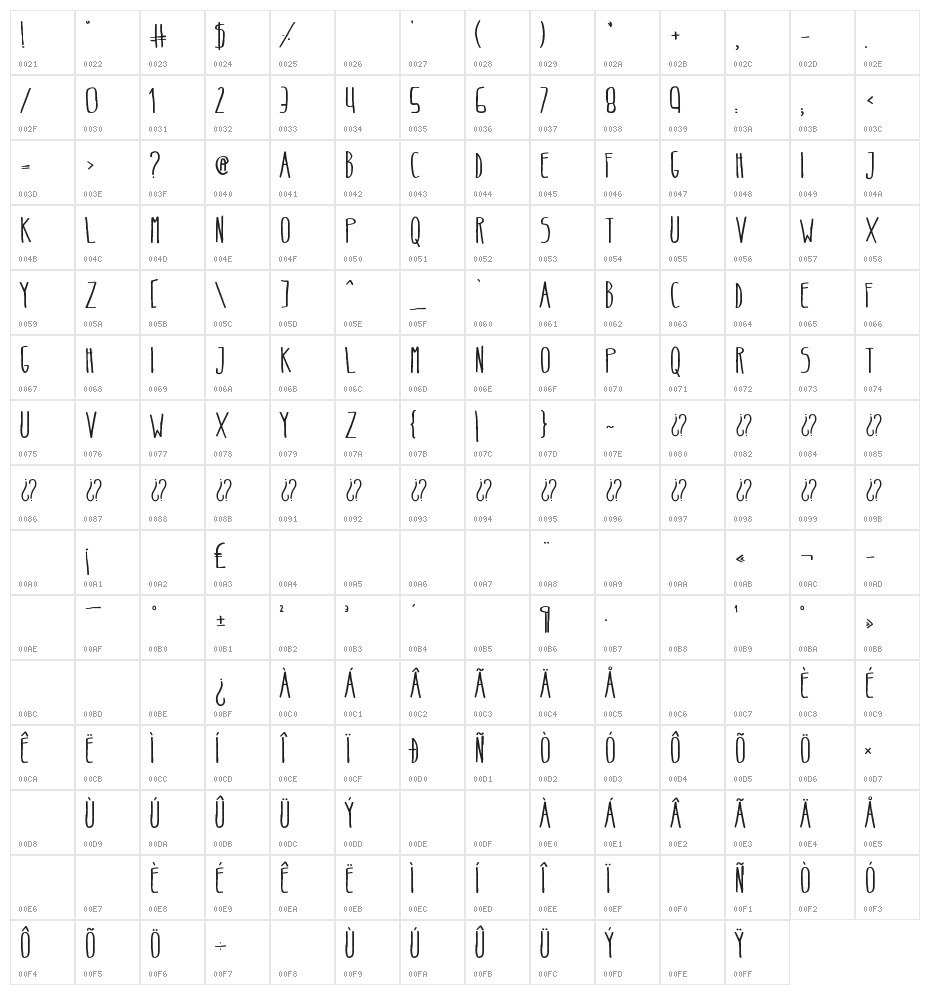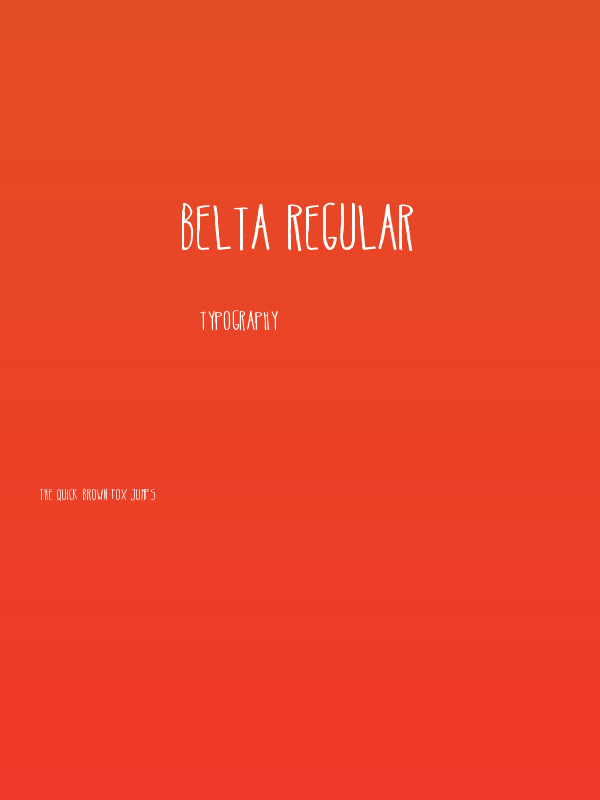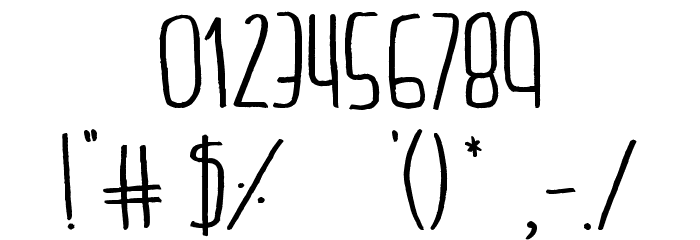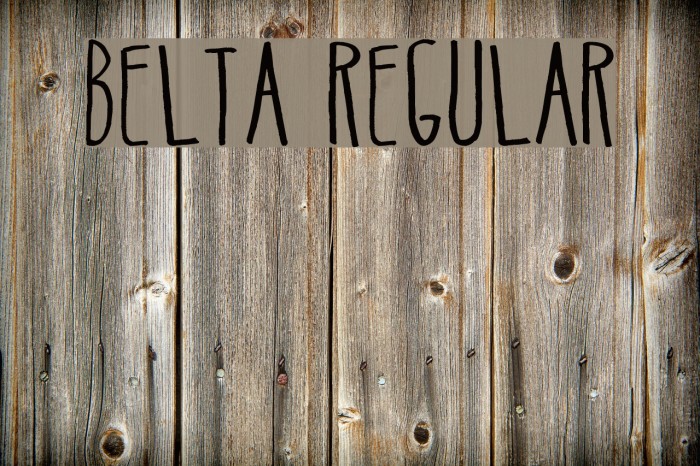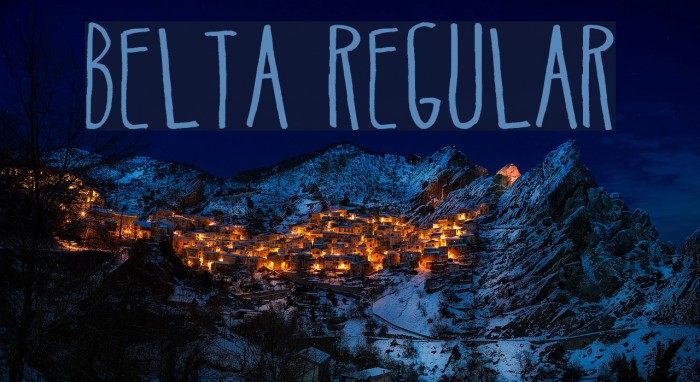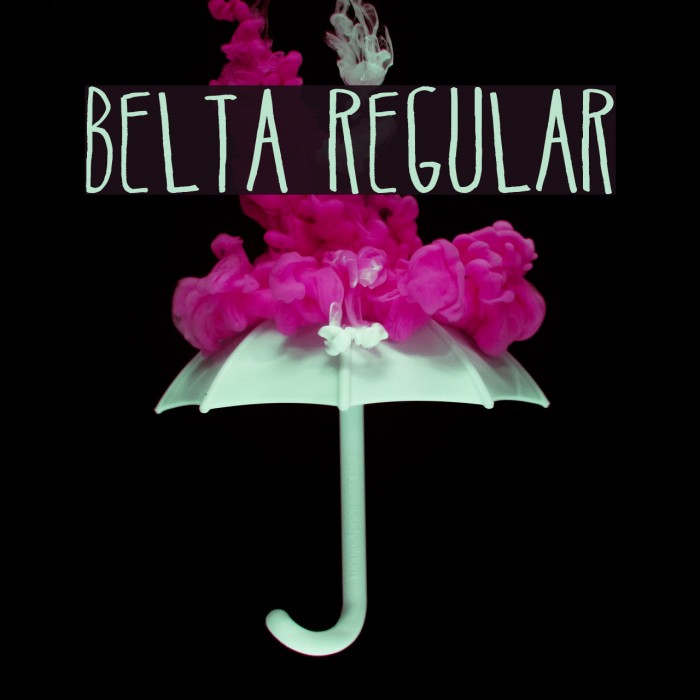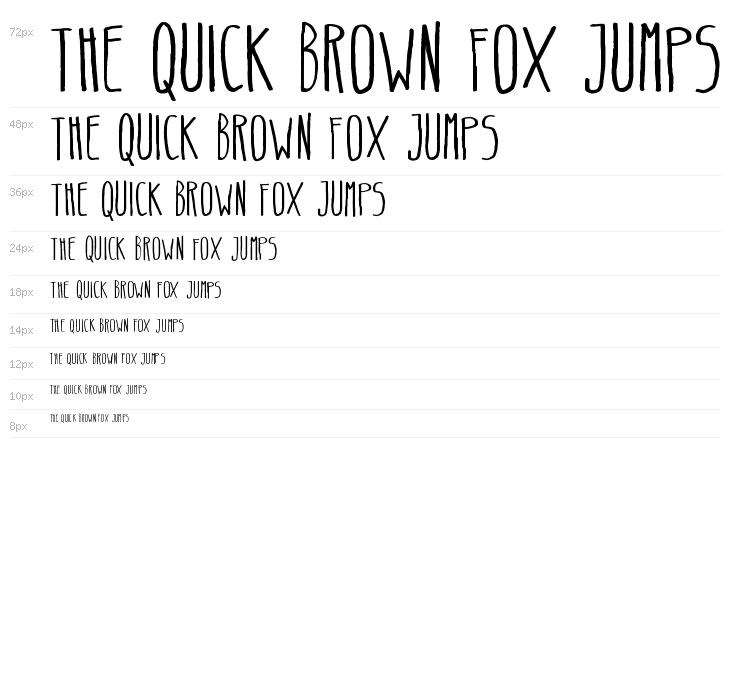
Belta Regular Font
Vanessa Bays
| Gesamtstil | Casual, Playful |
| Anwendungsfall | Headlines, Logos, Informal Text |
| Vorgeschlagene Projekte | Ideal for greeting cards, posters, children's books, and creative branding projects. |